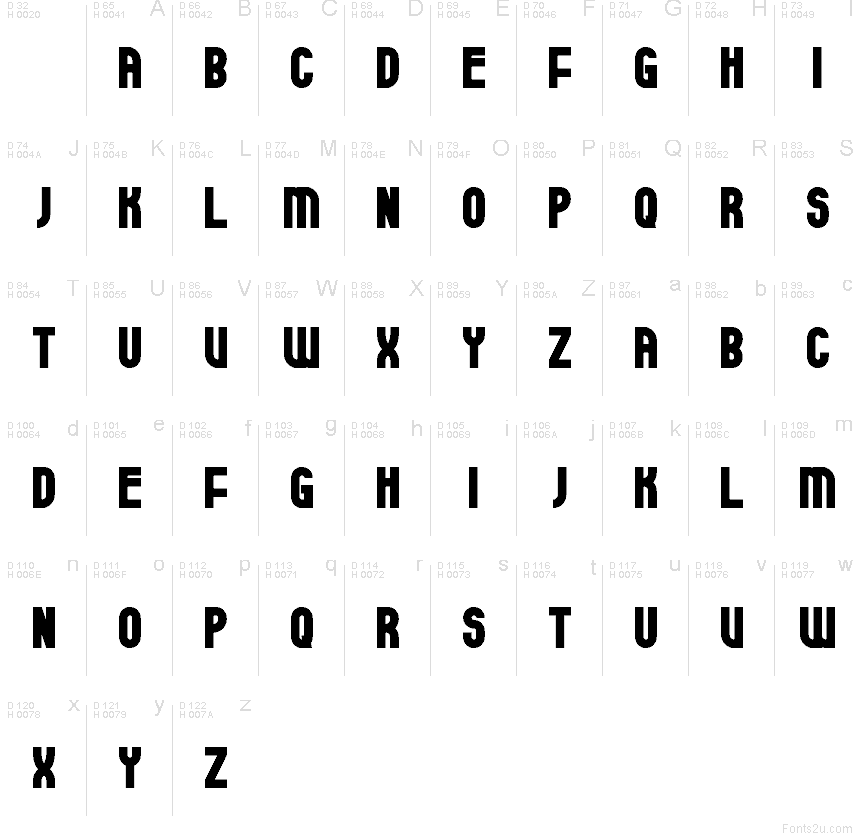
Retro Famous Bold od Vladimira Nikolica je bezplatné retro písmo typu display, které definují vysoké, masivní bloky, zaoblené vnější křivky a hluboké obdélníkové zářezy. Díky nim písmena nepůsobí jen široce, ale jako by byla vytesaná do materiálu. Písmo má díky své husté, plakátové siluetě charakteristický vzhled vintage nápisů, což ho odlišuje od jemnějších stylů připomínajících jídelní lístky v bistrech.
Tato kompaktní hmota vynikne zejména na plakátových titulcích, obalech alb, produktových obalech, výlohách obchodů a všude tam, kde písmo vyžaduje přímou grafickou roli. Krátká slova a skládané sazby těží z jeho hranatého rytmu, který dodává každému řádku stabilní, blokový pulz, aniž by působil zbytečně dekorativně.